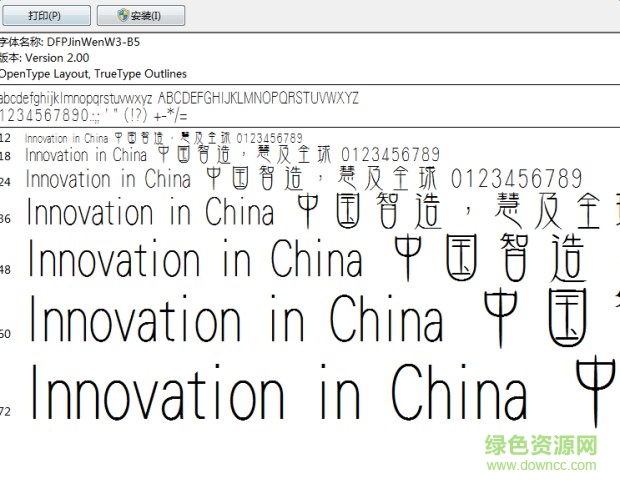
dfjinwen w3 winp bf字體又名華康金文體w3 p字體,是一款極具禪意的藝術(shù)字體,字形繁復(fù)線條靈動(dòng)灑脫,常常用作復(fù)古產(chǎn)品的包裝設(shè)計(jì)或平面設(shè)計(jì)方面,喜歡的朋友快來綠色資源網(wǎng)下載吧!
以戰(zhàn)國時(shí)期中山國所出土方壺上金文為發(fā)想,取其線條的韻律感,保留重心偏高的特點(diǎn),重組字體寫法,創(chuàng)造出古為今用的現(xiàn)代金文,整體予人端莊優(yōu)雅的形象,宛如清秀高䠷的古典美人。適合以女性為目標(biāo)的產(chǎn)品、包裝及名片,也適合具東方色彩的文宣刊物。
金文是指鑄造在殷周青銅器上的銘文,也叫鐘鼎文。商周是青銅器的時(shí)代,青銅器的禮器以鼎為代表,樂器以鐘為代表,“鐘鼎”是青銅器的代名詞。